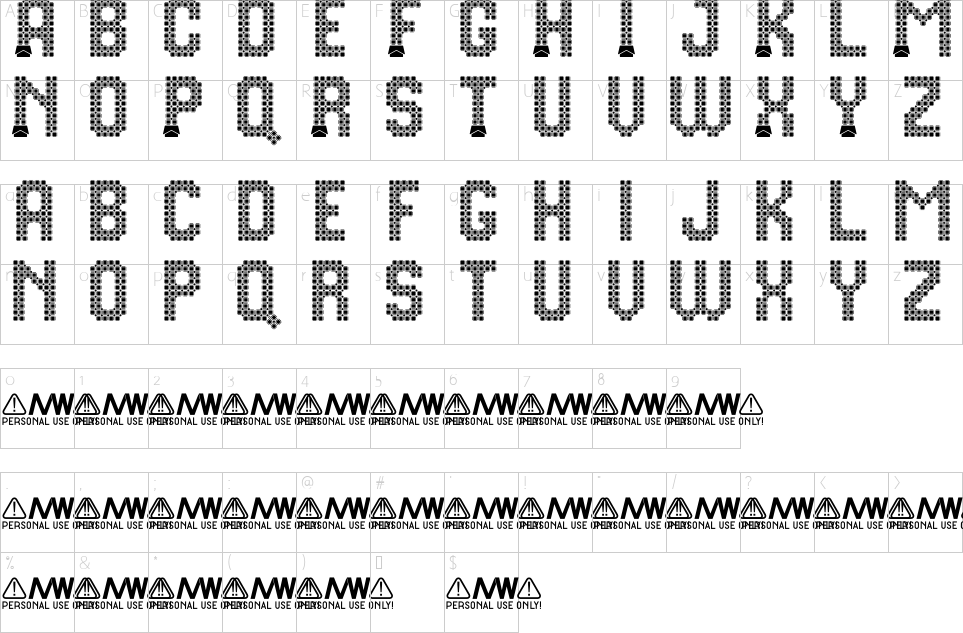
A Pixel Chocolate Font é uma deliciosa mistura de pixel art e chocolate, perfeita para adicionar um toque único a qualquer projeto. Desenhada pelo designer Máx Wynér, essa fonte gráfica é ideal para aqueles que valorizam a criatividade em cada projeto. Com sua design elegante e versátil, a Pixel Chocolate oferece um sorriso ao usuário ao criar textos personalizados. Com downloads superiores a mil, é claro que essa font é amada por designers e fãs de fontes gratuitas. Se você está à procura de uma fonte gráfica única e lúdica, a Pixel Chocolate é a escolha perfeita. Download hoje e experimente a saborosa experiência de trabalhar com essa font.